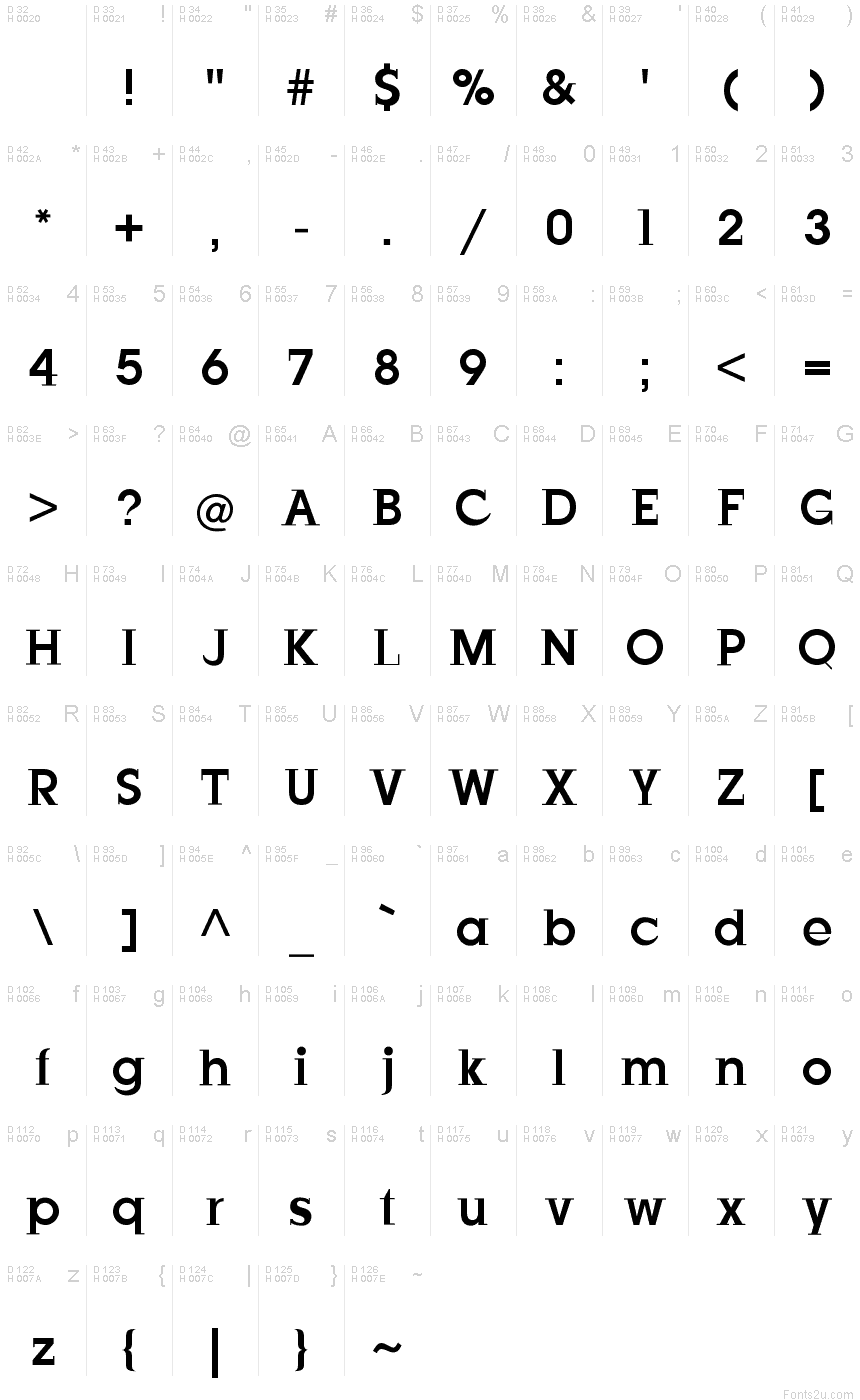
JustOldFashion
Just Old Fashion autorstwa Manfreda Kleina to bezpłatny krój szeryfowy o wyrazistym, teatralnym charakterze. Wysokie, proste kreski zderzają się z ogromnym, idealnie okrągłym „O”, nadając literom plakatową moc, a jednocześnie nawiązując do klasycznej tradycji drukarskiej. Kształty sprawiają wrażenie ciężkich i nasączonych farbą, jakby wyjęto je ze starej szuflady z czcionkami, jednak czyste krawędzie zapewniają ostry i nowoczesny wygląd.
Dzięki Just Old Fashion nagłówki nabierają ostrości i nuty vintage’owego dramatyzmu, nie wyglądając przy tym staroświecko. Ten darmowy font świetnie sprawdzi się na okładkach książek, etykietach win, plakatach teatralnych, w identyfikacji butików, na okładkach albumów i w tytułach redakcyjnych. Użyj go w dużym rozmiarze, aby pozwolić tym masywnym krzywiznom wybrzmieć, a w tekście głównym zestaw z lekkim, neutralnym krojem bezszeryfowym, co zapewni równowagę i czytelność.